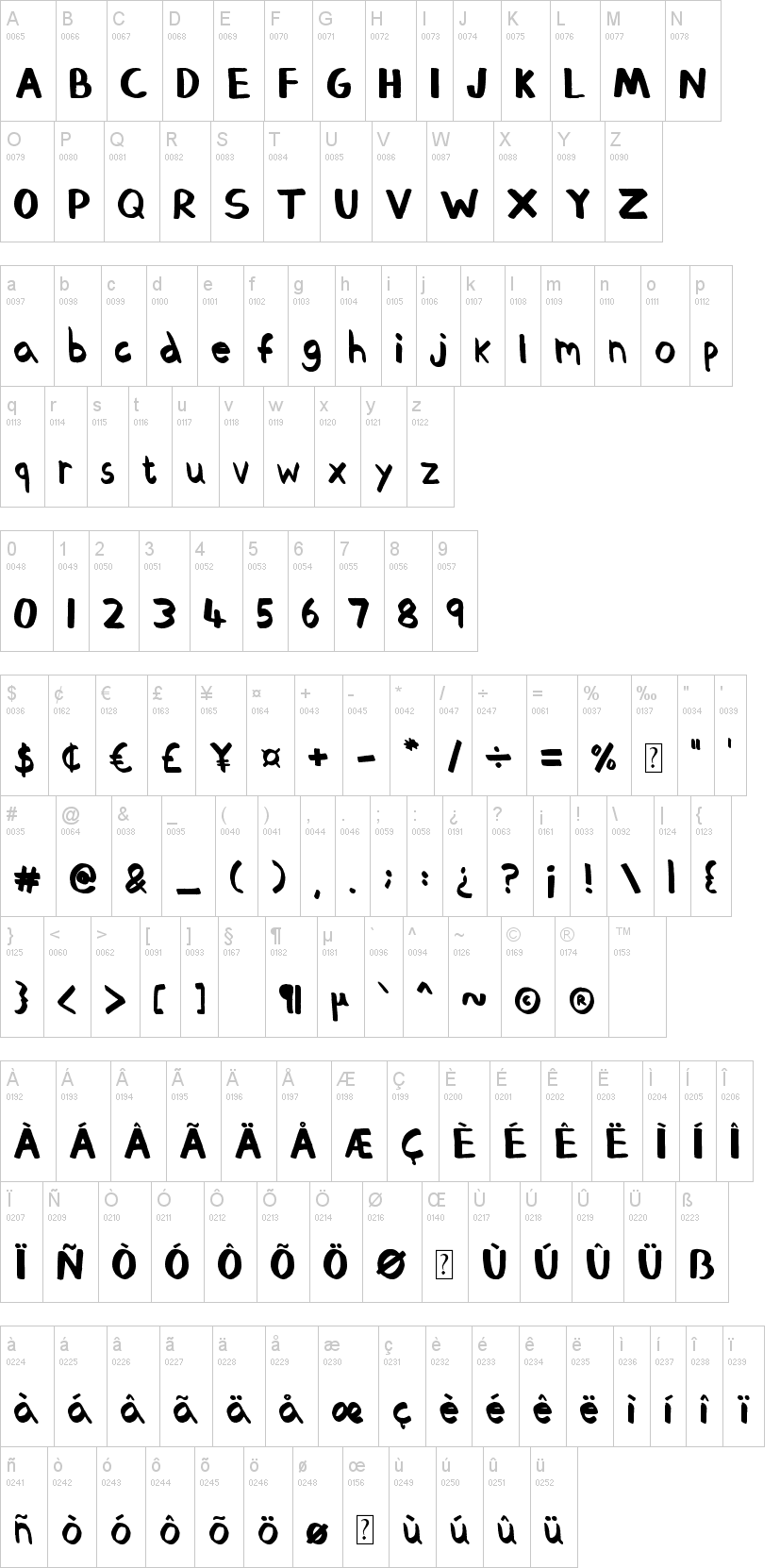
Thickedy Quick
Thickedy Quick是一款卡通字体,它具有鲜明的色彩和明快的线条,适合用于创建有趣的设计。字体的特点是其明快的线条,它可以使文字看起来更加吸引人,而且还可以增加设计的趣味性和记忆度。此外,卡通字体也可以用于创建更多样化的设计,从而吸引更多的客户。
Thickedy Quick是一款非常不错的手写艺术字体,具有很好的视觉感,适合于文化类的宣传设计、商业类品牌的广告和产品包装设计以及个性化文字排版等较多场景。